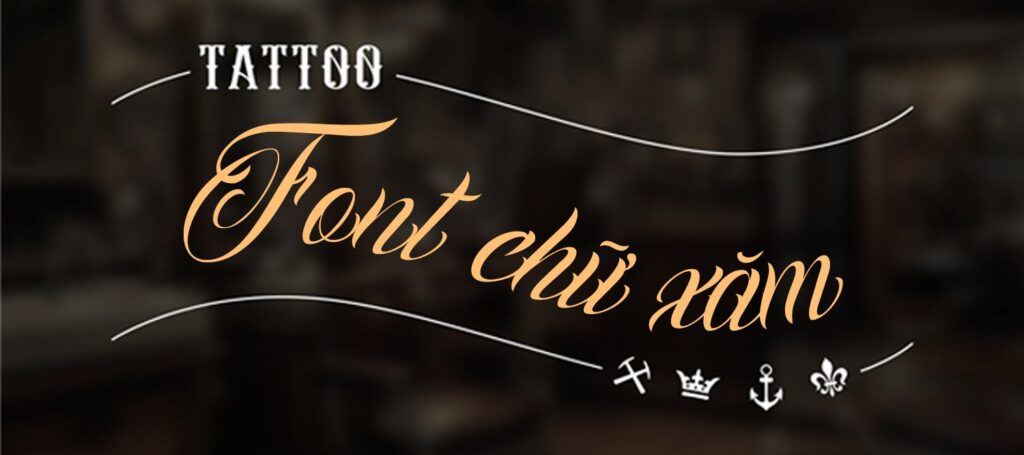
Font chữ tattoo là nhóm phông chữ đặc thù mô phỏng kỹ thuật điêu khắc mực trên da, nổi bật với phong cách Chicano Script uốn lượn hoa mỹ, chữ Gothic Blackletter gai góc hay các đường khắc số La Mã cổ điển. Mang vẻ ngoài phong trần, đậm tính cá nhân và giàu tính biểu cảm, font chữ xăm tattoo là chất liệu trực quan tuyệt vời để các kiến trúc sư, nhà thiết kế tạo dựng diện mạo ấn tượng cho các bản vẽ phối cảnh tiệm xăm nghệ thuật (Tattoo Studio) container, tiệm cắt tóc nam (Barbershop) hay các biển hiệu thời trang đường phố.
Nét khắc mực uyển chuyển và linh hồn nghệ thuật đường phố của font chữ tattoo
Điểm cuốn hút của phông chữ tattoo nằm ở sự kết hợp giữa nét cọ thư pháp phóng khoáng và kỹ thuật vuốt đuôi chữ phức tạp, tạo nên một dòng chảy thị giác lôi cuốn và đầy năng lượng. Từng con chữ sở hữu các đường lượn xoắn ốc tinh xảo, độ tương phản nét thanh nét đậm rõ nét và các chi tiết mũi nhọn sắc sảo mô phỏng đường kim xăm.
Sự ổn định về mặt cảm xúc của dòng font này giúp định hình phong cách bụi bặm, tự do và đề cao sự độc bản của người sử dụng không gian. Khi xuất hiện trên các bề mặt vật liệu kiến trúc thô ráp như vách tôn container sơn màu xám khói, tường gạch mộc, kính dán decal mờ hay gỗ thông sơn màu cháy rơm, kiểu chữ tattoo đẹp tạo nên sự tương thích thẩm mỹ đầy ma mị.
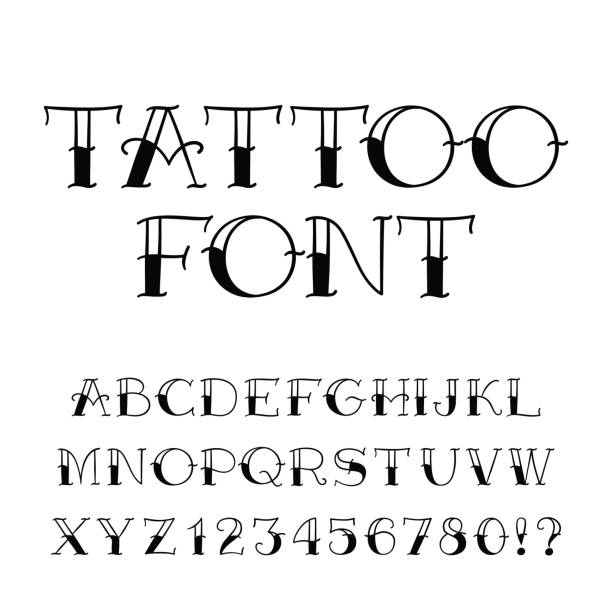
03 Ứng dụng phông chữ tattoo vào công trình thực tế
Nhờ diện mạo giàu tính biểu cảm và phong cách đường phố nổi bật, bộ phông chữ này mang lại giá trị thực tế lớn trong khâu tạo điểm nhấn cho các công trình hiện đại:
- Hệ thống biển hiệu cho Tattoo Studio và Barbershop Container: Những nét chữ uốn lượn Chicano của font chữ tattoo đẹp rất ăn ý khi gia công chữ nổi bằng inox vàng gương hoặc uốn đèn LED neon trên nền tôn đen mờ, mang lại diện mạo phong trần và thu hút khách hàng ghé thăm trải nghiệm.
- Bảng tên phòng và Biển chỉ dẫn phong cách Gothic: Phông chữ này khi gia công cắt laser trên các tấm kim loại rỉ sét hoặc khắc chìm trên gỗ sồi sẽ giúp các căn phòng trong khu nhà lắp ghép toát lên chất bí ẩn, tạo dấu ấn thị giác khó quên.
- Trang trí tranh tường và Bìa hồ sơ nghệ thuật đường phố: Bạn có thể dùng font chữ La Mã tattoo để ghi chú các mốc thời gian thành lập thương hiệu hoặc làm tranh trích dẫn trên tường panel, khơi gợi tinh thần làm việc nhiệt huyết và đam mê sáng tạo.
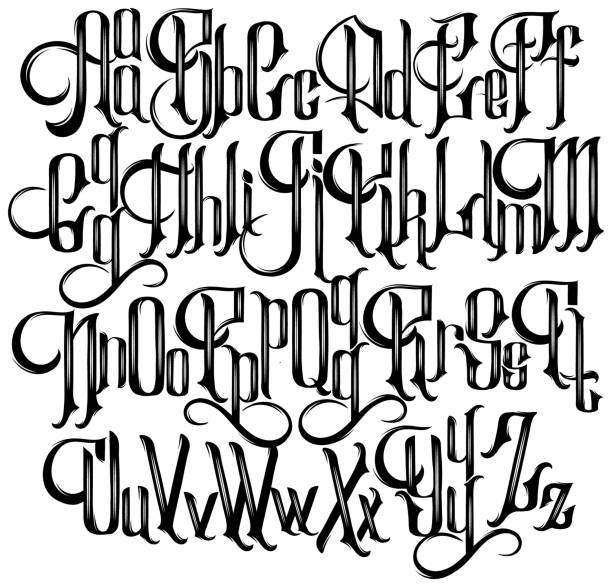
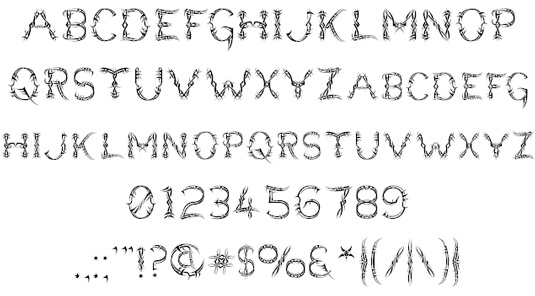
03 Lưu ý bố cục font chữ tattoo đẹp luôn sắc nét và có chiều sâu
Để khai thác hiệu quả vẻ đẹp của dòng font xăm nghệ thuật này mà không gây cảm giác rối rắm cho bản vẽ, người thiết kế nên lưu tâm một số kinh nghiệm sau:
- Tránh viết hoa toàn bộ ký tự: Các chữ cái in hoa của dòng chữ Chicano hay Gothic có độ xoắn và vươn dài rất lớn. Việc viết hoa liên tiếp nhiều chữ cái sẽ làm các nét móc đè chồng lên nhau, gây mất trật tự bố cục và làm câu văn trở nên khó nhận diện.
- Bố trí khoảng trống rộng rãi: Bạn nên chừa khoảng thở thoáng đãng xung quanh tiêu đề để các đường đuôi chữ uốn lượn có không gian lan tỏa thị giác, tránh để các chi tiết đồ họa phụ trợ chèn ép câu chữ.
- Kết hợp cùng gam màu trầm đậm: Phông chữ phát huy hiệu quả thị giác cao khi phối cùng các tông màu mang sắc thái mực xăm như đen tuyền, đỏ bordeaux, xám khói hoặc vàng ánh kim trên nền tối, làm nổi bật đường nét sắc sảo của bộ chữ.